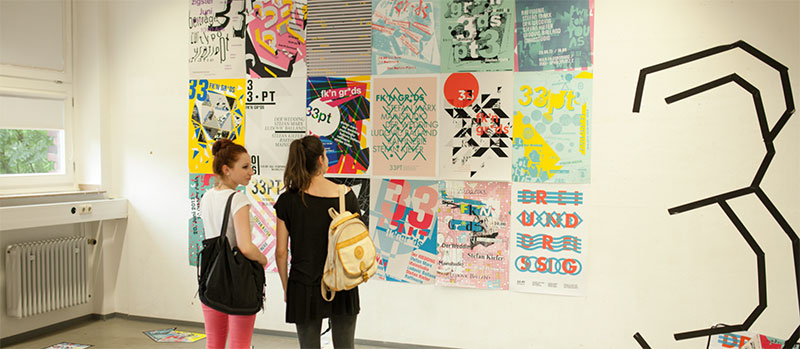
Von Hand geschriebene Briefe
Ausstellung im Druckkunst-Museum Leipzig
24. April bis 3. Juli 2016
Eröffnung: 22. April, 19 Uhr, in Anwesenheit von Jost Hochuli
Die Ausstellung vereint Briefe von den 1940er Jahren bis in die ersten Jahre des 21. Jahrhunderts, die von Grafikern, Typografen, Schriftgestaltern und Verlegern geschrieben wurden. Gezeigt werden sie weniger wegen ihres Inhalts, sondern vielmehr wegen ihrer Schrift. Es handelt sich um Handschriften, deren Schreiber sich mit der Schriftreform des Engländers Alfred Fairbank (1895–1982) beschäftigt und nach dessen Vorlagen ihren eigenen handschriftlichen Ausdruck geformt haben.
Gegen Ende des 19. Jahrhunderts setzte sich die englische Arts-and-Crafts-Bewegung für eine Erneuerung aller Zweige des Kunstgewerbes ein; Handarbeit sollte soweit wie möglich die mechanisch produzierten Industrieerzeugnisse ersetzen. In dieser Tradition schuf Alfred Fairbank nach 1921 die Grundlagen für die später nach ihm benannte Handschriftenreform.
Mit „A Handwriting Manual“ veröffentlichte er 1932 die erste umfassende Darstellung seiner Ideen. Wichtige Eigenschaften wie das Schreiben mit der Breitfeder, die Betonung von Über- und Unterlängen sowie eine geringe Schriftneigung nach rechts charakterisieren das „Fairbank’sche Modell“.
Die in der Ausstellung präsentierten Briefe von Alfred Fairbank, Anna Hornby, Paul Standard, Jan van Krimpen, Jan Tschichold, Hans Schmoller, Max Caflisch und Gerrit Noordzij und anderen an Walter Käch, Rudolf Hostettler, Jost Hochuli und Jan Tschichold zeigen die Rezeption der schriftreformerischen Ideen Alfred Fairbanks und belegen die Vielgestaltigkeit der Umsetzung.
Die Ausstellung umfasst rund 40 Briefe, die einer Privatsammlung mit etwa 400 handgeschriebenen Briefen entstammen. Kuratiert wurde die Schau vom Schweizer Grafiker und Buchgestalter Jost Hochuli.
Der Katalog „Einige von Hand geschriebene Briefe“
(VGS Verlagsgenossenschaft St. Gallen und Jost Hochuli, 2013)
Führung 60+ am Dienstag, 24. Mai, 15 Uhr
Öffentliche Führung am Sonntag, 3. Juli, 12 Uhr
33pt. Fest für Typografie, Grafik und Gestaltung33pt / I don´t care
22. Juni 2016 - 24. Juni 2016
Dortmund + Köln
33pt, das Fest für Typografie, Grafik und Gestaltung an der FH Dortmund und der Köln International School of Design (KISD), geht in die nächste Runde. Auch in diesem Sommer werden Gäste aus ganz Europa mit Vorträgen und Workshops begeistern – und das in gewohnt ungewohnter 33pt-Atmopshäre.
In diesem Jahr erwarten Euch die Sprecher im Hotel LivInn (Im Zentrum von Dortmund, 2 Minuten vom Hauptbahnhof entfernt, direkt neben dem DFB Museum). Ob auf dem Bett oder Tiger-Teppich, im Schrank oder Bad – ihr seid herzlich eingeladen, im gemütlichen Hotelzimmerflair den Sprechern zuzuhören.
In Köln findet 33pt an der KISD statt.
MIittwoch 22. Juni 2016
WORKSHOPS DORTMUND
01_ Für Hier / Nordstadtgalerie Dortmund
02_ Fount Magazine / Ort wird nach Anmeldung noch bekannt gegeben
03_ Workshop an der FH Dortmund
Donnerstag 23. Juni 2016, 14:00
VORTRÄGE + TALKS
HOTEL LIVINN / DORTMUND
Moniteurs / Sybille Schlaich / Berlin / D
Swiss Type / Ian Party / Lausanne / CH
Optik / Jens Müller / Düsseldorf / D
Herburg Weiland / Tom Ising / München / D
Isabel Seiffert / Zürich / CH
Freitag 24. Juni 2016, 09:30
VORTRÄGE
Köln International School of Design (KISD)
Ubierring 40, 50678 Köln
www.kisd.de
Moniteurs / Sybille Schlaich / Berlin / D
Tino Graß / Köln / D
Tim & Tim / Berlin / D
Paul Steinmann und David Eckes / Köln D
Uwe Loesch / Düsseldorf / D
Underware / Den Haag / NL
Roosje Klap / Amsterdam / NL
Koptisch gut! Eine Einführung in die koptische Buchbindetechnik
In dem eintägigen Workshop werden wir uns allgemeine Werkzeuge und Materialien, die zum Handwerk der Buchbinderei gehören anschauen, ausprobieren und dann in einer koptischen Bindung anwenden. Die koptische Bindung ist eine der ältesten Techniken um Bucheinbände zu fertigen. Sie geht zurück bis ins vierte Jahrhundert n. Chr. ! Das besondere ist die Buchdecke, welche direkt in den Kettenstich eingebunden wird. So lässt sich das Buch am Ende flach aufschlagen.
Auftrag und Wirkung der typografischen Komposition
Martin Mosch
Vom Dialog der bedruckten und der unbedruckten Fläche. Schrift ist die Voraussetzung zur typografischen Gestaltung. Jedoch spielt die eigentliche Anordnung als Komposition eine ganz dominante Rolle.